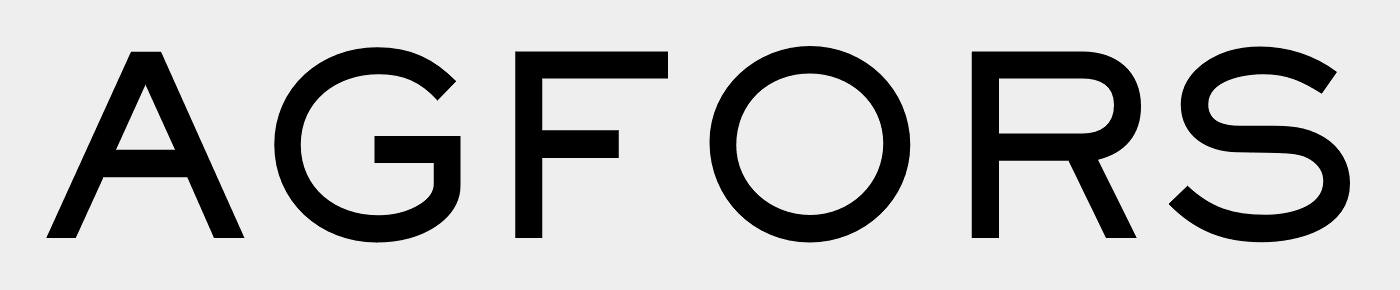
...rundes G und abgerundete Ecken...
Ein Kunde möchte, dass ich weiteren Text in der  im Logo verwendeten Schriftart für ihn setze. - Dazu wäre es schlau, wenn ich wüsste, welche er (bzw. sein Grafiker) verwendet hat...
Jemand eine Idee?
Ich hatte erst die Trio Grotesk im Verdacht – ist es allerdings nicht. Wenn man die Ecken der ITC Blair abrundet, kommt man der gesuchten Schrift sehr nahe.
Wenn wir wüssten, woher das stammt, kämen noch ein paar Such-Wege infrage. Das Logo ist  dem weltweiten Netz ja leider nicht bekannt …
Das Logo gehört zu einem kleinen Restaurant in Hagfors, Värmland, Schweden. Es heisst Brukshotellet.
Die abgerundeten Ecken hätte ich wirklich gern übernommen.
Die wirken auf mich wie nachträglich in Illustrator, InDesign, … über eine Runde-Ecken-Funktion hinzugefügt. Solltest Du hinbekommen. :-)